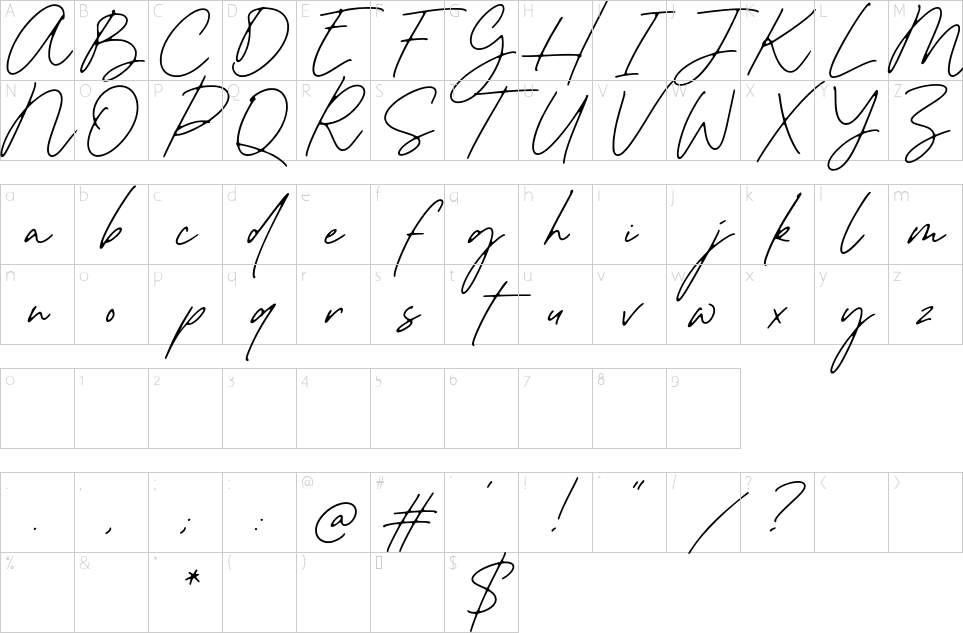
Autographer Font – Fonte Grátis
Autographer Font
A Autographer é uma fonte moderna e elegante que surge perfeita para qualquer projeto de design gráfico. Com um design minimalista e sofisticado, esta fonte é ideal para criar layouts profissionais, desde sites até capas de livros. Ela foi projetada pelo estúdio Letteralle Studios, uma equipe talentosa que oferece uma variedade de fontes para o uso profissional e pessoal. Com seu design cuidadosamente elaborado, a Autographer torna o processo de design mais gratificante e eficiente. Atualmente, esta fonte tem sido descarregada mais de 5,788 vezes, demonstrando seu valor e popularidade no mercado. Sem dúvida, esta fonte adiciona um toque único e sofisticado a qualquer projeto que escolha. Descubra a autenticidade e a elegância que esta fonte pode trazer para seu trabalho. Sua descarga agora começa.
Mapa de caracteres da fonte Autographer Font